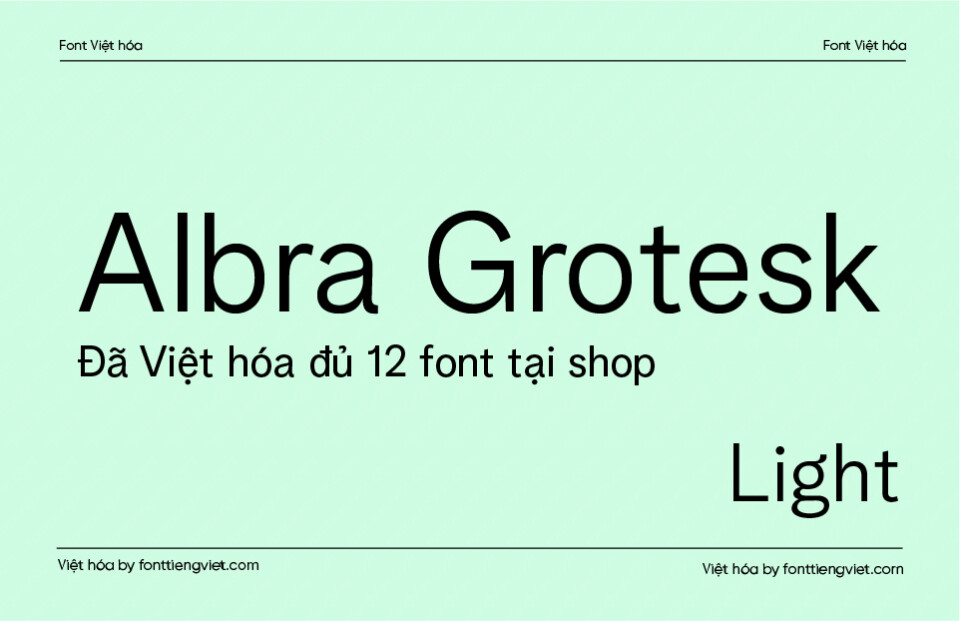
Tải Font Việt hóa 1FTV VIP Albra Grotesk Light Miễn Phí Cho Thiết Kế Hiện ĐạiGiới thiệu về Font Việt hóa 1FTV VIP Albra Grotesk LightTrong thế giới thiết kế đồ họa hiện đại, việc lựa chọn một bộ Font Miễn Phí chất lượng luôn là ưu tiên hàng đầu của các nhà sáng tạo. Đặc biệt là đối với cộng đồng thiết kế tại Việt Nam, nhu cầu tìm kiếm những bộ font chữ không chỉ đẹp mà còn phải hỗ trợ đầy đủ tiếng Việt một cách mượt mà là rất lớn. Một trong những cái tên đang thu hút sự chú ý gần đây chính là Font Việt hóa 1FTV VIP Albra Grotesk Light. Đây là một phiên bản font chữ đặc biệt, mang phong cách tối giản, tinh tế nhưng vẫn giữ được sự sang trọng cần thiết cho các ấn phẩm chuyên nghiệp. Với độ dày nét mảnh (Light), bộ font này giúp các bản thiết kế trở nên thanh thoát và dễ nhìn hơn bao giờ hết.Tại sao nên sử dụng Font Việt hóa 1FTV VIP Albra Grotesk LightĐặc điểm thiết kế tinh tế và hiện đạiFont Việt hóa 1FTV VIP Albra Grotesk Light thuộc họ font Grotesk, vốn nổi tiếng với cấu trúc chữ cái rõ ràng, không chân và mang hơi thở của thời đại mới. Phiên bản Light mang đến một cảm giác nhẹ nhàng, phù hợp để làm phần nội dung (body text) cho các trang web cao cấp, tạp chí thời trang hoặc các bài thuyết trình tại trường học. Các ký tự được chăm chút tỉ mỉ, khoảng cách giữa các chữ cái được căn chỉnh khoa học, giúp người đọc không bị mỏi mắt khi theo dõi những đoạn văn bản dài. Điều này cực kỳ quan trọng trong môi trường giáo dục, nơi mà sự rõ ràng của con chữ luôn được đặt lên hàng đầu.Khả năng tương thích và tối ưu hóa tiếng ViệtĐiểm mạnh nhất của bộ Font Việt hóa 1FTV VIP Albra Grotesk Light chính là quá trình Việt hóa chuyên nghiệp từ đội ngũ 1FTV. Các dấu câu tiếng Việt như dấu huyền, sắc, hỏi, ngã, nặng được thiết kế lại để cân đối hoàn hảo với các chữ cái gốc, tránh tình trạng dấu bị quá cao hoặc quá thấp làm hỏng bố cục tổng thể. Điều này giúp các bạn học sinh và giáo viên có thể yên tâm sử dụng trong các bài báo cáo, Slide giảng dạy hay các thiết kế poster sự kiện trường học mà không lo lỗi font hay sai lệch hiển thị trên các thiết bị khác nhau.Ứng dụng thực tế của Font Việt hóa 1FTV VIP Albra Grotesk LightSáng tạo nội dung số và in ấnNhờ vẻ ngoài thanh lịch, Font Việt hóa 1FTV VIP Albra Grotesk Light rất được ưa chuộng trong việc thiết kế giao diện ứng dụng (UI/UX) và website. Nó tạo ra một không gian trắng thoáng đãng, giúp thông tin được truyền tải một cách trực quan nhất. Bên cạnh đó, trong lĩnh vực in ấn, font chữ này thường được dùng cho các thiệp mời, brochure giới thiệu sản phẩm hoặc bìa sách nghệ thuật. Sự tối giản của Albra Grotesk Light giúp các yếu tố đồ họa khác được nổi bật hơn mà không làm mất đi tính thẩm mỹ chung của toàn bộ tác phẩm thiết kế.Kết luận về bộ Font Việt hóa 1FTV VIP Albra Grotesk LightViệc sở hữu bộ Font Việt hóa 1FTV VIP Albra Grotesk Light trong thư viện font chữ của mình sẽ giúp bạn nâng tầm các sản phẩm thiết kế lên một đẳng cấp mới. Sự kết hợp giữa phong cách châu Âu hiện đại và sự tinh tế của tiếng Việt đã tạo nên một công cụ hỗ trợ đắc lực cho mọi dự án sáng tạo. Hy vọng rằng với những chia sẻ trên, bạn đã có cái nhìn rõ nét hơn về giá trị mà bộ font này mang lại. Nếu bạn đang tìm kiếm một nguồn tài nguyên uy tín, hãy ghé thăm Font Miễn Phí, Font Việt Hóa, Font Việt hóa 1FTV VIP Albra Grotesk Light để tải về và trải nghiệm ngay hôm nay. Chúc các bạn có những tác phẩm thiết kế thật ấn tượng và thành công.
Font Việt hóa 1FTV VIP Albra Grotesk Light